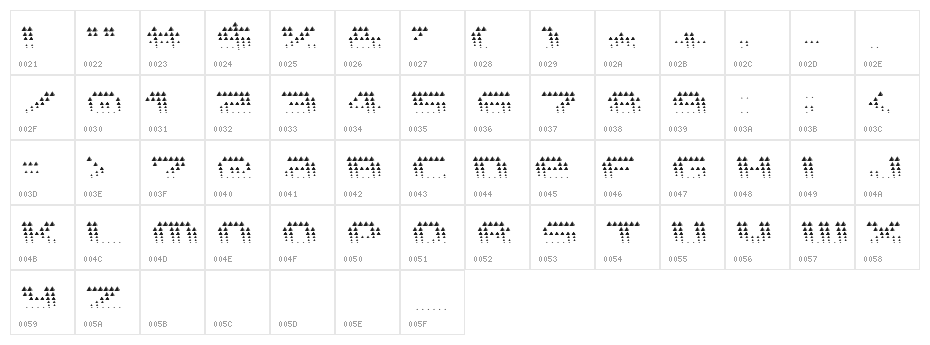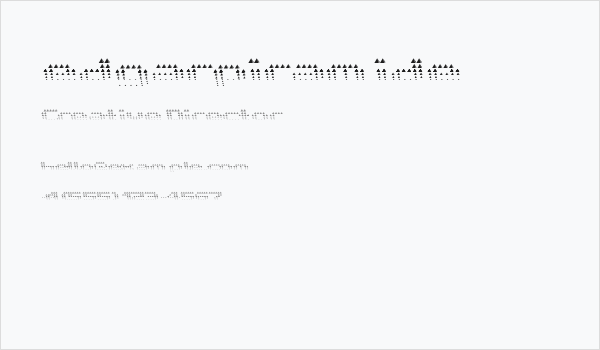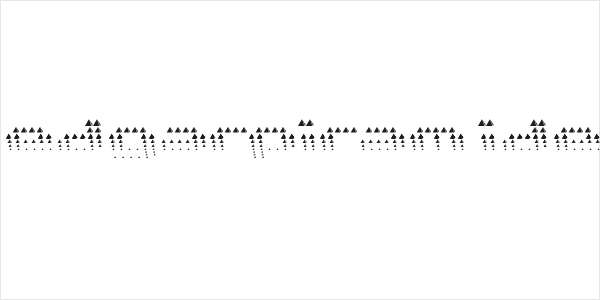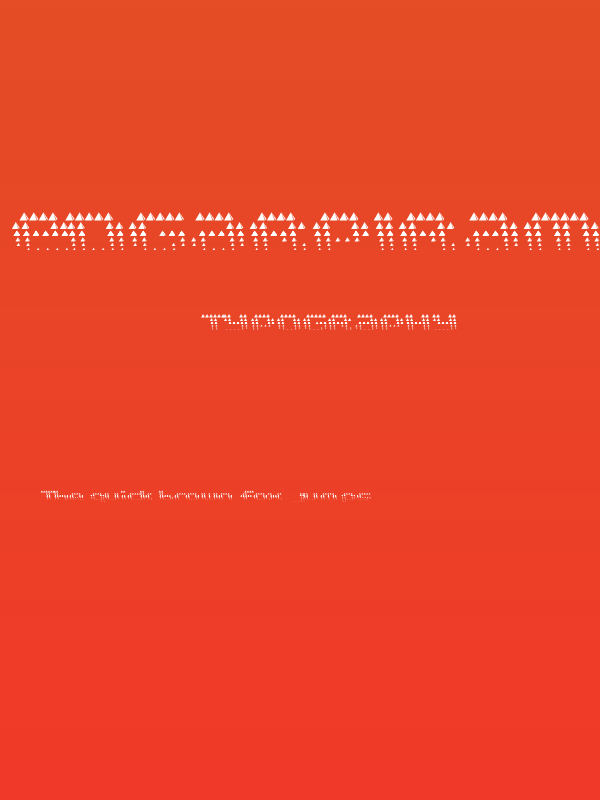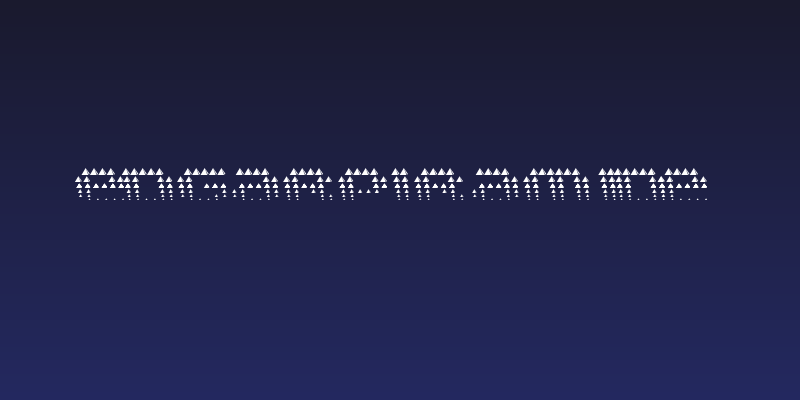
edgarpiramide Font
EDGARPIRAMIDE MAIUSCOLE
EDGARPIRAMIDE MINUSCOLO
EDGARPIRAMIDE ALTRI CARATTERI
| Nome | edgarpiramide |
| Progetti proposti | This font is perfect for artistic posters, unique branding projects, album covers, and any design work that aims to capture attention with a bold, geometric style. |